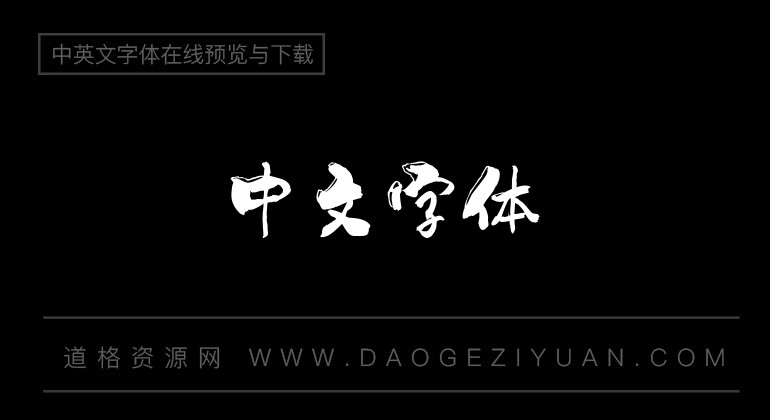
潮字社虎头啸简
潮字社虎头啸简是一款由潮字社推出的字体,它是一款具有中国传统特色的字体,具有浓郁的文化底蕴和深厚的历史积淀。字体的笔画细腻,线条优美,笔锋活跃,给人以清新、自然的感觉,是一款非常适合用于广告、商标、品牌等设计的字体。
潮字社虎头啸简是一款非常不错的手写艺术字体,具有很好的视觉感,适合于文化类的宣传设计、商业类品牌的广告和产品包装设计以及个性化文字排版等较多场景。